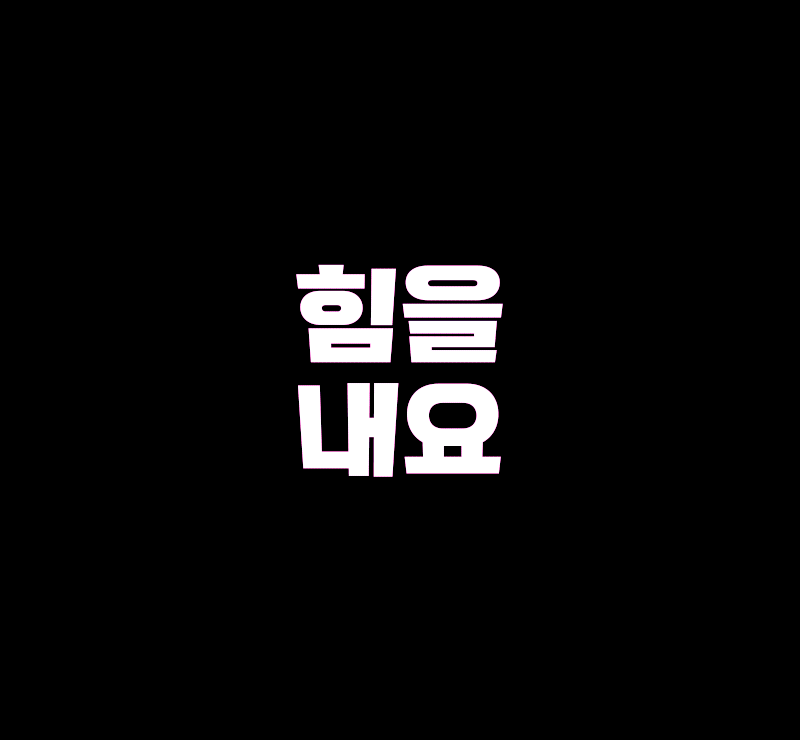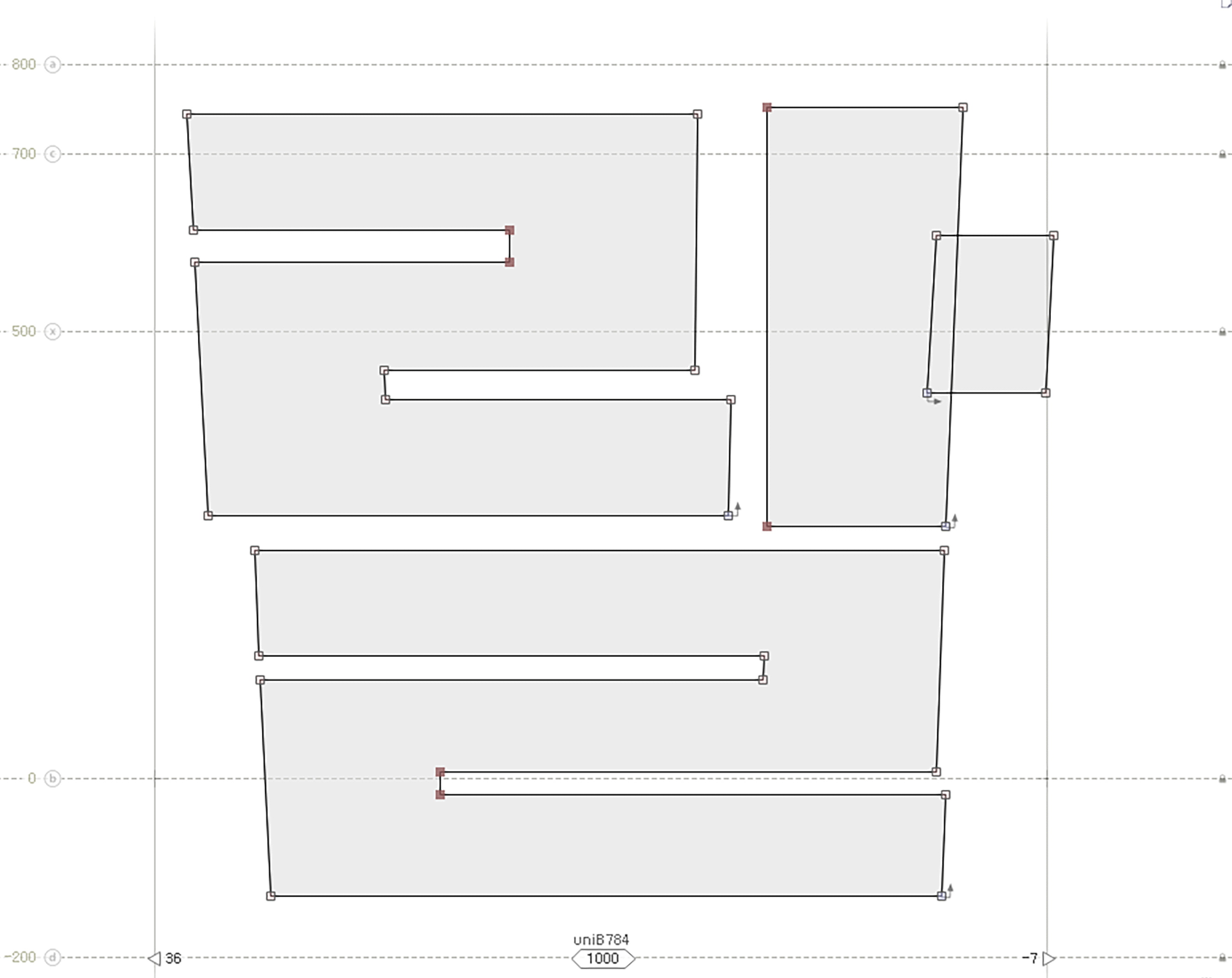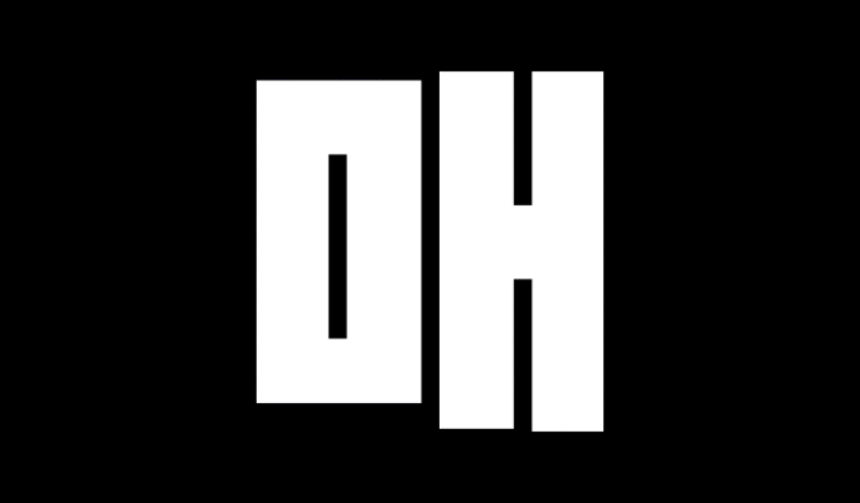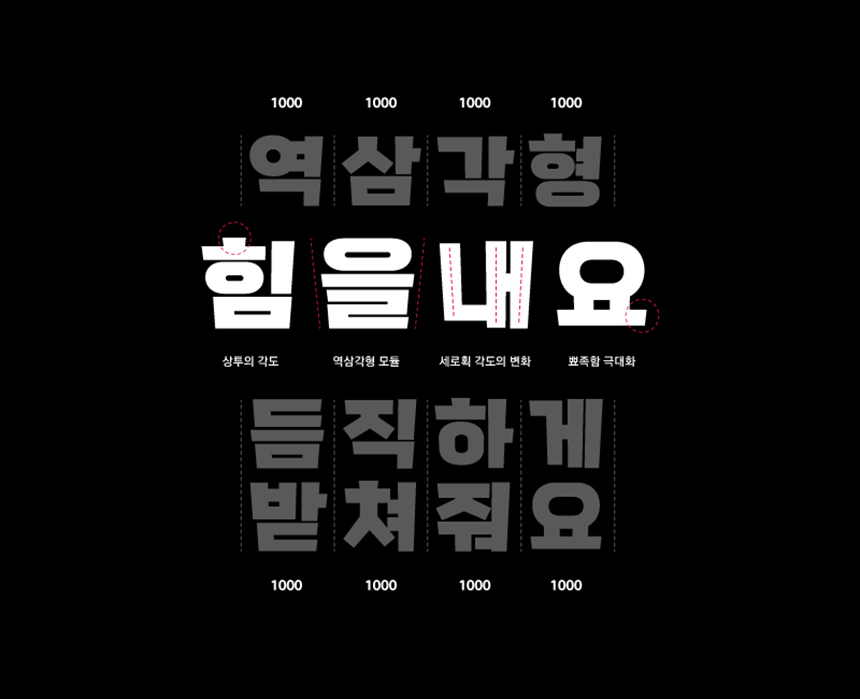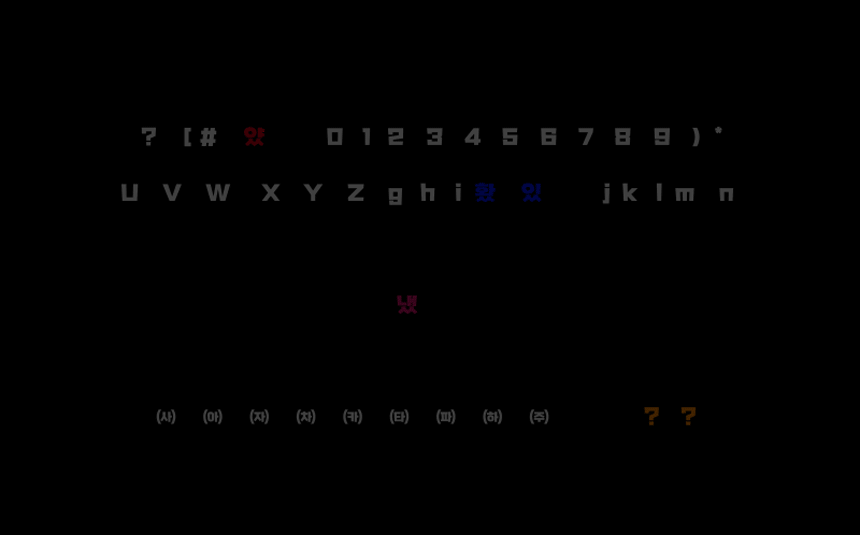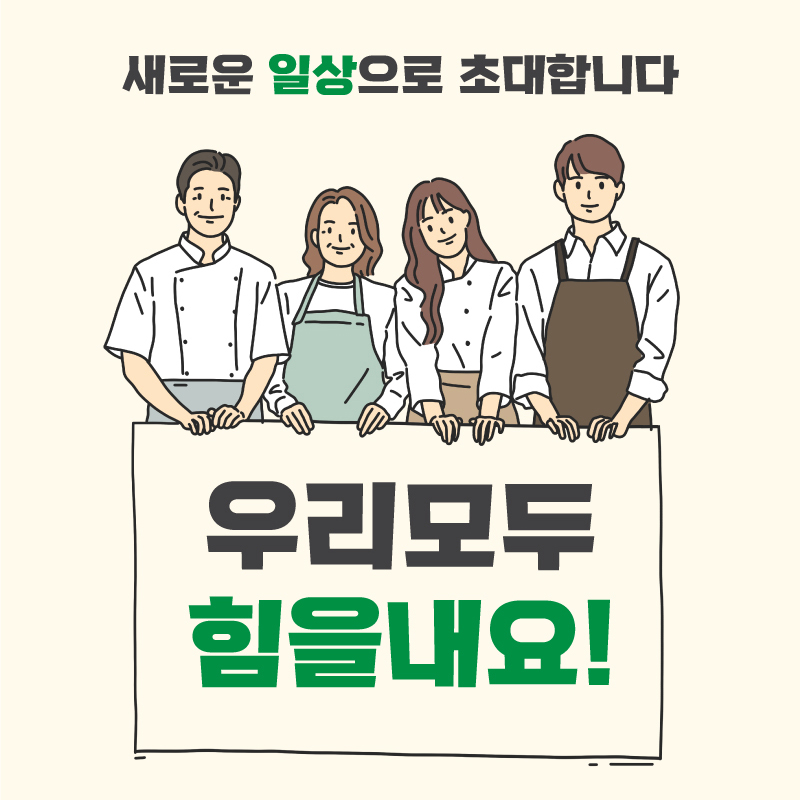
서로에게 건네는 힘찬 위로
안녕하세요. 어느새 차가운 바람이 불어오는 계절입니다. 함께하는 일상이 좀처럼 나아지지 않아 더 춥게 느껴지는 겨울, 우리 모두 힘을 내자는 의미로 제작한 12월의 신규 폰트 「Rix힘을 내요」를 소개합니다! 단단하고 두꺼운 굵기와 독특하고 디자인적인 형태로 눈길을 끄는 제목용 서체 'Rix힘을내요'를 제작한 이수하 디자이너와의 인터뷰를 담아봤습니다.
안녕하세요. 12월 신서체 Rix힘을내요 폰트를 제작한 이수하라고 합니다.
2021년의 마지막 신서체 Rix힘을내요, 어떻게 기획하게 되셨는지 궁금해요!
12월 신서체 Rix힘을내요는 코로나로 힘든 시기를 보내는 모든 분들에게 응원을 보낸다는 의미로 폰트 그 자체에 메시지를 담은 서체인데요. 든든한 슈퍼맨의 역삼각형 로고에서 아이디어를 얻어 같은 역삼각형 모듈로 제작한 단단하고 파이팅 넘치는 서체입니다.
Rix힘을내요 폰트에서 특별히 좋아하는 포인트가 있다면?
이번 힘을내요 서체는 역삼각형 모듈이 가장 큰 포인트며, 그 부분을 더 확실하게 주기 위해 좌우 가로획 끝의 사선을 더 과하게 만들었습니다. 이 부분을 후반 작업으로 하나하나 만지는 것이 힘들고 시간이 더 걸렸지만 완성 후 처음에 생각했던 느낌이 더 잘 살려진 것 같아 좋았습니다.
요즘은 외국 서체 디자인을 보며 여러 가지 영감을 얻습니다. 영문은 한글과 다르기 때문에 곡선과 획의 대비를 자유롭게 이용한 디자인이 많아 재미있고, 한자와 일어는 필법 디자인 요소들이 획이 많아질 때 어떠한 규칙을 적용하는지 찾아보며 참고하게 됩니다.
힘을 내요, 슈퍼 파워!
Rix힘을내요는 굵고 두꺼운 획으로 구성되어 글자 하나 하나에 힘이 느껴지도록 디자인된 서체입니다. 슈퍼맨의 이미지가 연상되도록 역삼각형 형태로 제작해 강인하고 든든한 모습을 표현하고자 했습니다.
위쪽에서 아래쪽으로 좁아지는 역삼각형 모듈로 과한 사선으로 설계된 디자인이 특징인 서체입니다. 두껍고 묵직한 획과 가파른 각도가 시선을 사로잡아 다른 서체들과의 차별성을 줍니다.
역동적인 제목용 서체
기본적으로 동일한 폭을 가진 넓은 고정폭을 갖고 있어 안정적이게 받쳐주지만, 과하지 않은 디자인을 접목해 특징이 확실한 서체입니다. 상투의 각도나 뾰족한 획 처리 등 포인트가 되는 부분을 세심하게 작업했습니다. 전체적인 디자인으로 보았을 때 역동적인 이미지를 줄 수 있는 제목용 서체입니다.
영문, 숫자, 약물 또한 한글의 역동적이고 독특한 디자인을 그대로 적용했습니다. 다양한 활용을 위해 약물 986자로 개발하여 여러 조합으로 재미있게 사용할 수 있습니다💪💪
| 이렇게 활용해 보세요
다시 함께하는 일상을 위한 노력이 요즘 많이 이뤄지고 있죠. 주목성이 요구되는 배너, 문구가 강조되어야 하는 포스터, 인쇄물 등에 텍스트로 활용해 보세요.
눈길을 확 끌어줄 썸네일이 필요한가요? 단단하고 두꺼운 웨이트가 시선을 사로잡기에 충분합니다. 요즘에는 자막에도 크고 굵직한 서체를 쓰는 경향이 있기 때문에 타이틀이나 자막 상관없이 자유롭게 활용하기 좋습니다.
오늘 소개해드린 Rix힘을내요 폰트는 2021년 마지막을 장식하는 신서체인만큼 많은 분들께 힘이 되었으면 하는 마음으로 힘 있고 무게감 있는 폰트로 제작했습니다. 서체명처럼 모두가 힘을 낼 수 있는 연말연시가 되었으면 좋겠네요!